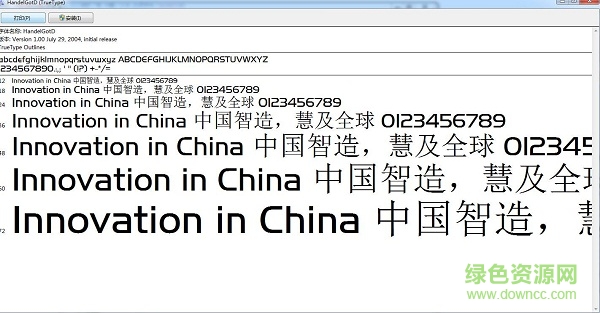
handelgotd bold
handelgotd字體包收錄了handelgotd bold和handelgotd regular兩款無(wú)襯線字體,字體特征鮮明,弧線漂亮,可以電子產(chǎn)品、平面設(shè)計(jì)、海報(bào)設(shè)計(jì)等領(lǐng)域,需要的朋友快來(lái)下載吧!
無(wú)襯線字體介紹
它以幾何學(xué)的方式確立漢字的基本結(jié)構(gòu)(它是構(gòu)建性的,而非書(shū)寫(xiě)性的),其均勻的筆劃寬度和平滑的筆劃弧度表現(xiàn)出一種穩(wěn)定的、充滿機(jī)器意味的無(wú)時(shí)間性及共時(shí)性特征!
handelgotd bold
無(wú)襯線字體特征
有相同的曲率;
筆直的線條;
銳利的轉(zhuǎn)角。